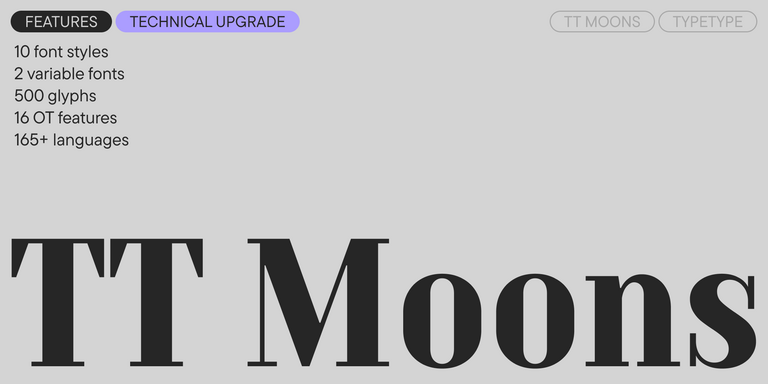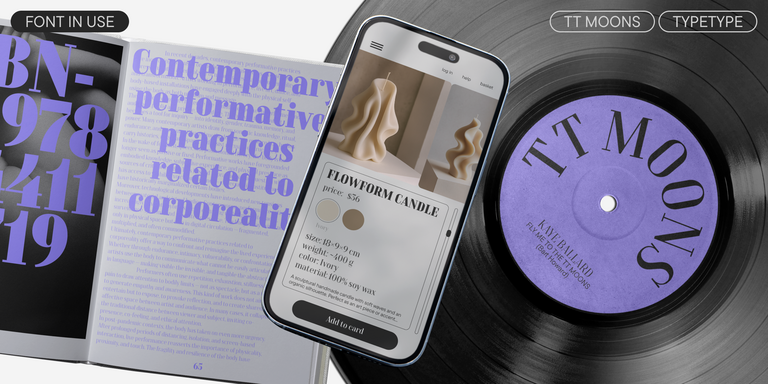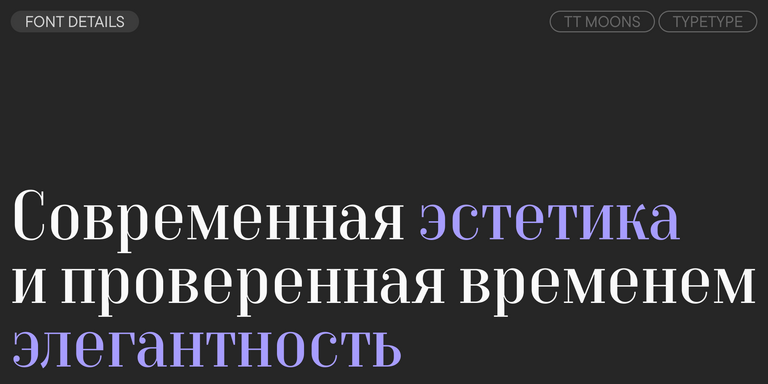
TT Moons — узкая и контрастная антиква. Данное шрифтовое семейство очень элегантно работает в классических темах дизайна. TT Moons по стилистике относится к глиптальным новостильным шрифтам. Идеальная сфера использования TT Moons — это верстка журналов, книг и газет.